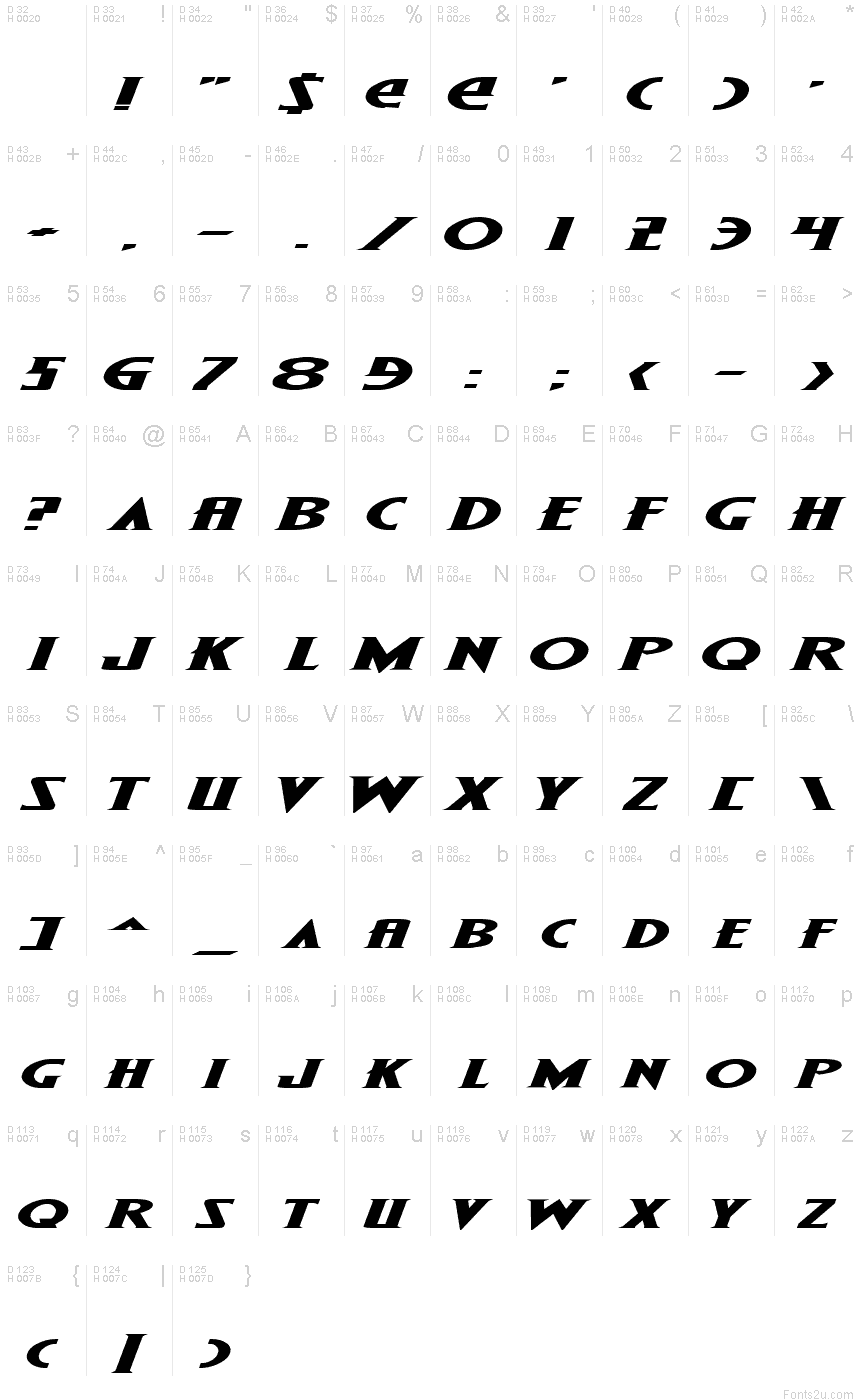
Wolf's Bane Expanded Italic von Iconian Fonts ist eine kostenlose retro Sci-Fi-Display-Schrift mit der direkten Wucht eines alten Actionfilm-Plakats. Die Buchstaben sind stark geneigt und breit gezogen; eine Mischung aus scharfen Ecken, massiven Diagonalen und weitläufigen Kurven, die an 70er-Jahre-Paperbacks, Arcade-Automaten und Pulp-Serien erinnert.
Es passt perfekt auf Spiele-Logos, Comic-Cover, Plakat-Überschriften, Titelkarten und Merch-Grafiken – überall dort, wo es mehr auf Attitüde als auf Feinheiten ankommt. Als Free-Font eignet es sich zudem hervorragend für kurzes Branding, Kapitelanfänge und Monogramme, da die übertriebenen Neigungen und spitzen Schnitte die Großbuchstaben selbst bei kurzen Texten lebendig wirken lassen.
Wolf's Bane Expanded Italic